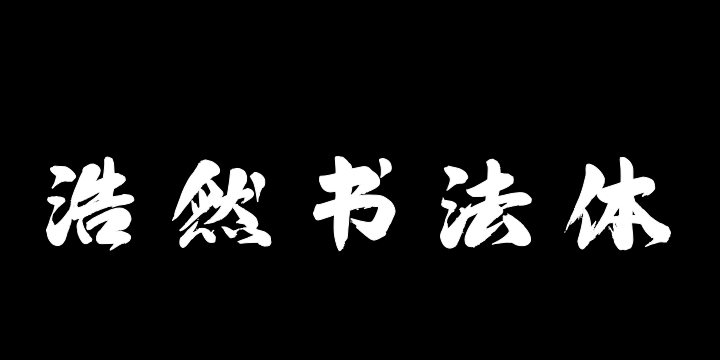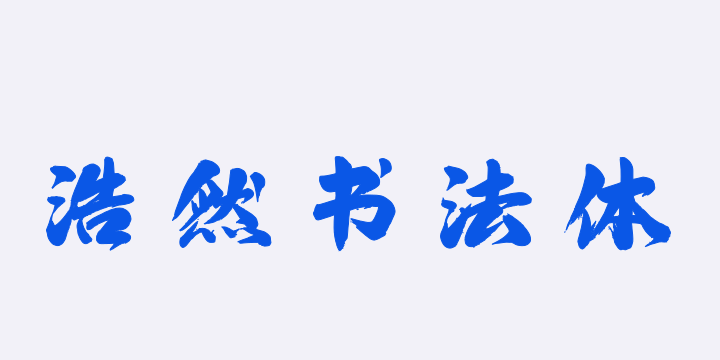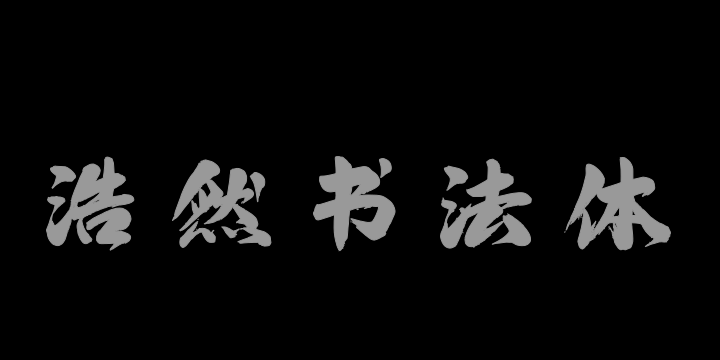
上首浩然书法体 By 上首造字 商用字体
字体全名: 上首浩然书法体
铸字厂: 上首造字
设计师: 胡博剑
字体简介: 上首浩然书法体,简体中文约6763字,字体笔画苍劲有力,粗细收方有度。整体上的造型饱满,潇洒豪迈,笔画出入间尽显大师风范,既保留了传统书法的气韵,又具有设计感,给人一种安心踏实、波澜壮阔的感觉。适用于搭配标志、广告标语、商业广告等高端属性。